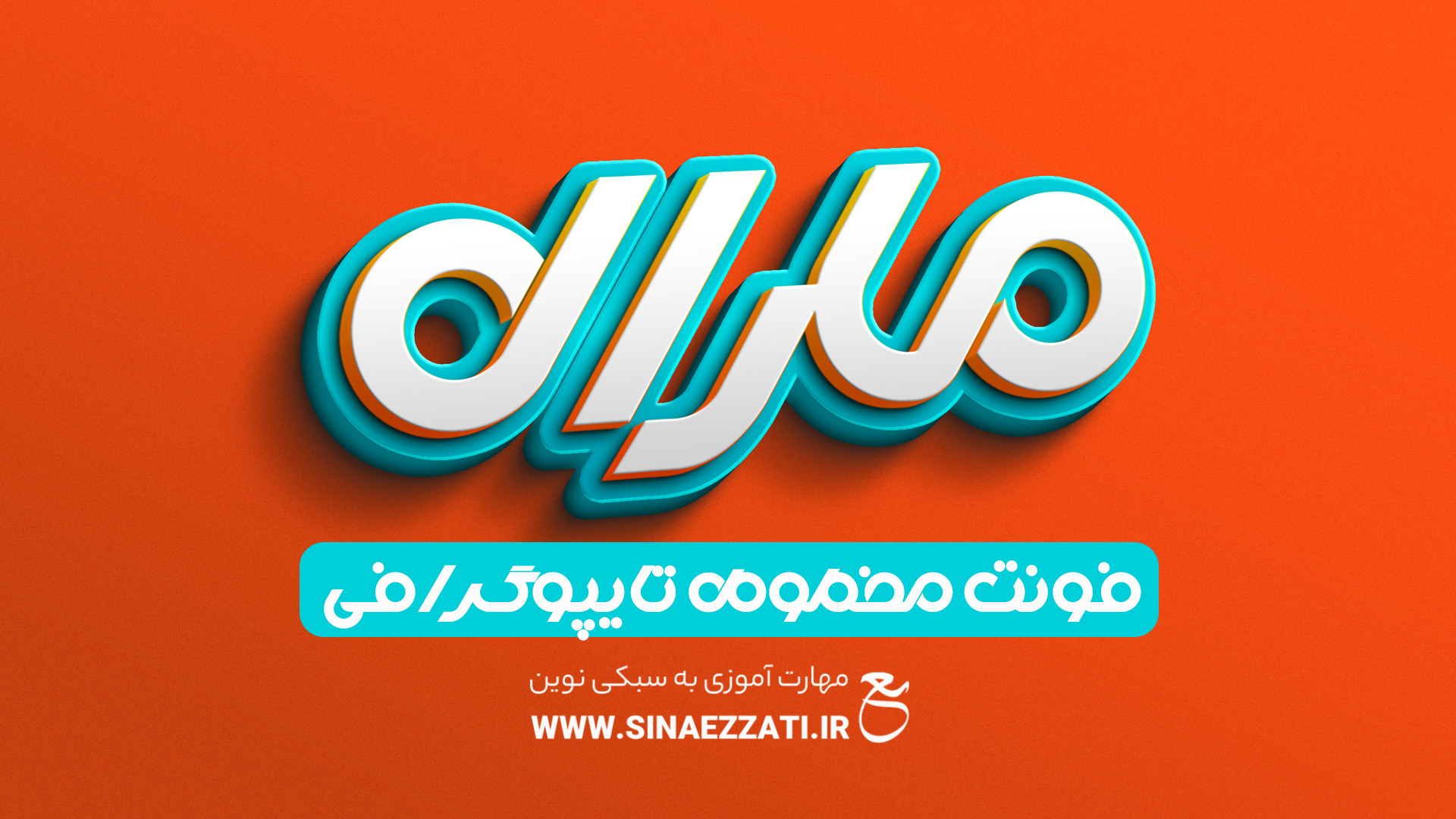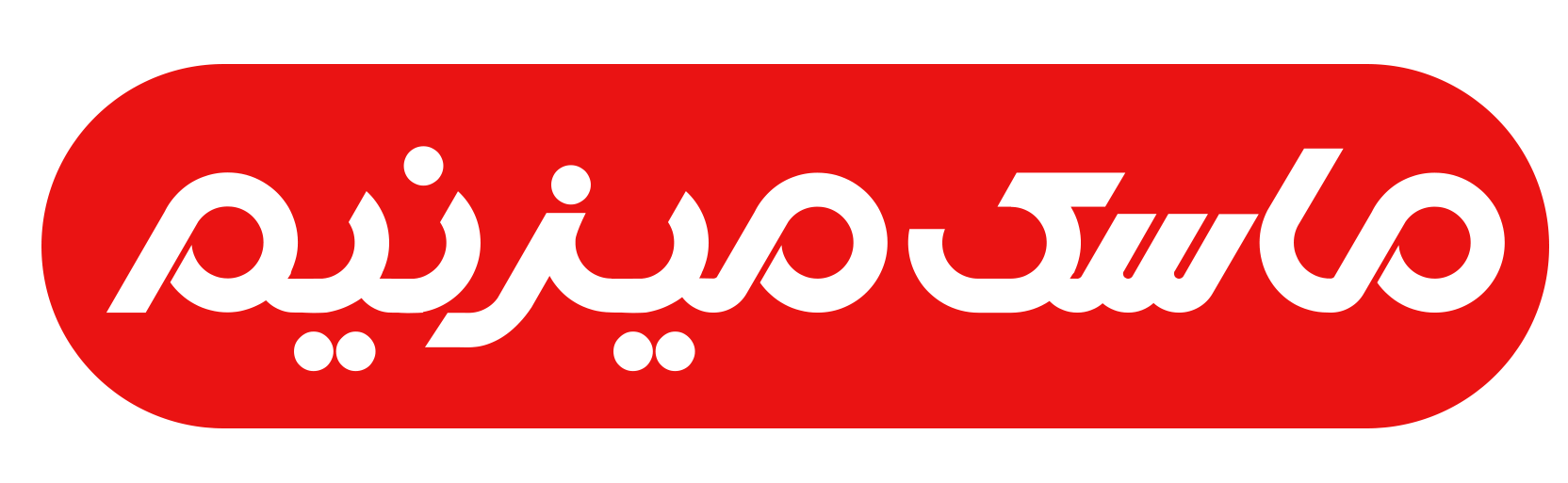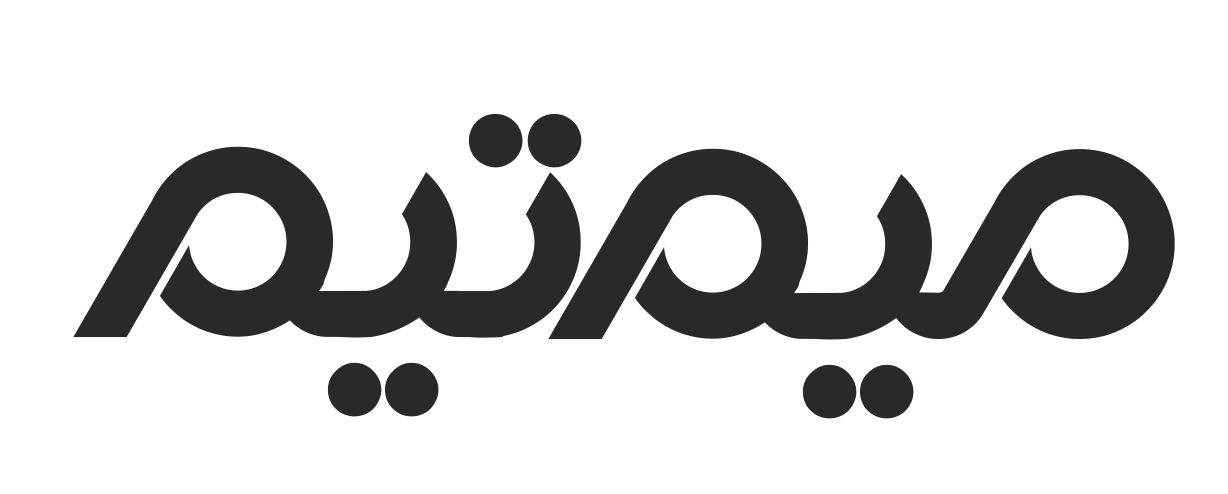
فونت تایپوگرافی مارال
فونت تایپوگرافی فارسی مارال با طراحی منحصر به فرد و حروفی پویا، به شما این امکان را میدهد که تایپوگرافیهای خلاقانه و لوگوتایپهای جذاب را به راحتی خلق کنید و توجه هر بینندهای را به خود جلب کنید. این فونت به شما اجازه میدهد در کمترین زمان، تایپوگرافیهای شگفتانگیزی ایجاد کنید و برای دستیابی به بهترین نتیجه، پیشنهاد میشود در نرمافزارهایی مانند فتوشاپ، ایلاستریتور و کورل دراو از آن استفاده کنید تا بتوانید با شخصیسازی، طرحهای خاصی به مشتریان خود ارائه دهید.
✅ مناسب برای طراحیهای تایپوگرافی و لوگوتایپهای فانتزی.
حالت های مختلف فونت مارال